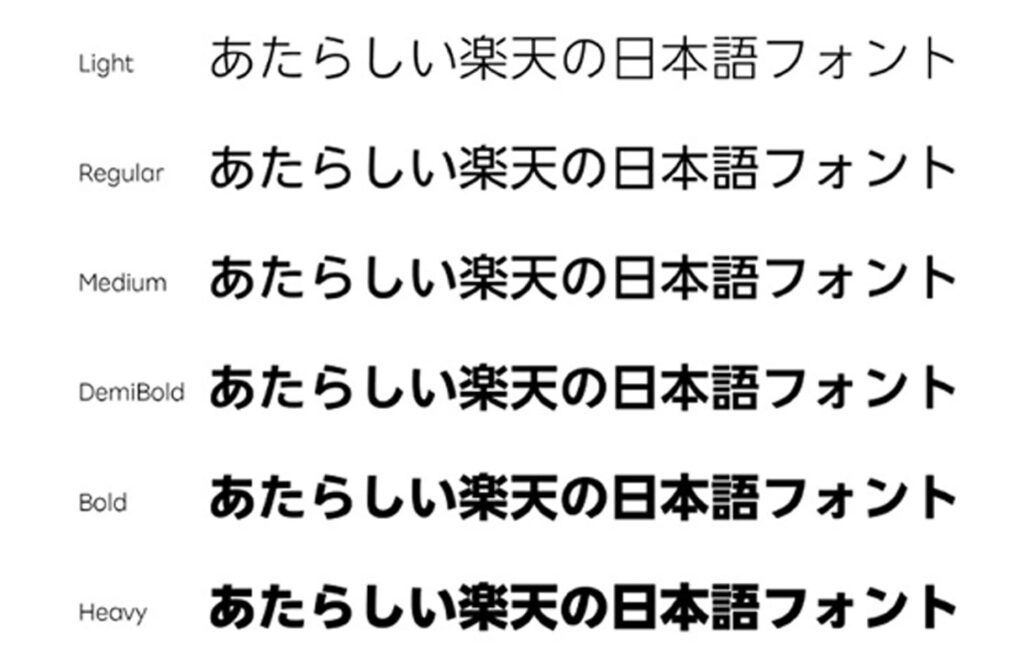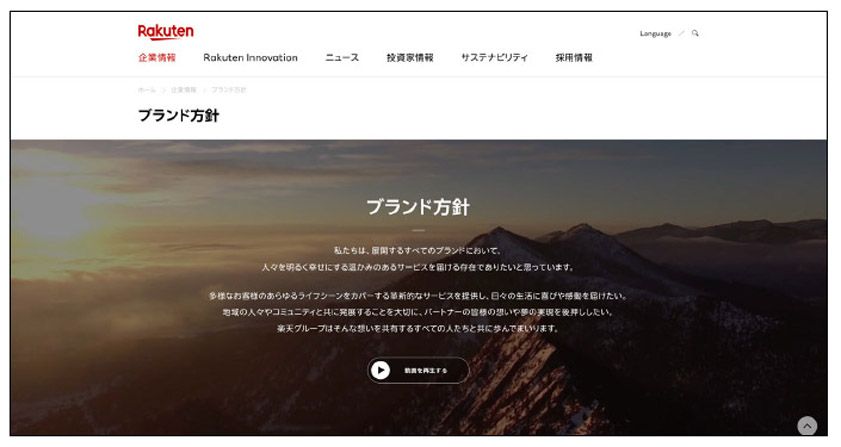
モリサワ 楽天の日本語コーポレートフォント「Rakuten Sans JP」を共同開発、コーポレートサイトに実装
株式会社モリサワは、楽天グループ株式会社とともに、日本語コーポレートフォント「Rakuten Sans JP」を共同開発した。「Rakuten Sans JP」は3月から、楽天のコーポレートサイトの一部で使用されている。
楽天は、国内外において、Eコマース、トラベル、デジタルコンテンツなどのインターネットサービス、クレジットカードをはじめ、銀行、証券、電子マネー、スマホアプリ決済といったフィンテック(金融)サービス、携帯キャリア事業などのモバイルサービス、さらにプロスポーツといった多岐にわたる分野で70 以上のサービスを提供。楽天会員を中心とした独自のメンバーシップを有機的に結びつけることで、独自の「楽天エコシステム(経済圏)」を形成しています。また、「イノベーションを通じて、人々と社会をエンパワーメントする」というミッションのもと、ユーザーや社会に向けてさまざまなメッセージを発信してきた。
そのブランド価値の向上を図る一環として、2020 年に開発された欧文コーポレートフォント「Rakuten Font」と、モリサワが提供する「UD 新ゴNT」の日本語フォントが主に運用されてきた。
そしてこの度、日本語での情報発信においても、より一層ブランドの統一感を表現するため、日本語コーポレートフォントの開発も行うこととなり、楽天グループの戦略的ブランディングにおいてクリエイティブ面をリードする組織「楽天デザインラボ」および多数のコーポレートフォント開発実績もあるモリサワとの共同開発が実現した。
「Rakuten Sans JP」は、欧文コーポレートフォント「Rakuten Font」のサンセリフ書体である「Rakuten Sans」との親和性を持たせながら、チーフクリエイティブデザイナー佐藤可士和氏の監修のもと、楽天のブランド方針やTone of Voice を体現するデザインとなっている。
これまで使用されてきた「UD 新ゴNT」をベースに、欧文エリアを「RakutenSans」に合わせ、すべてのかなに独自のデザインを施すことで、オリジナリティとこれまで通りの読みやすさを追求した。社名である「楽」「天」の漢字2 文字の字形も、楽天ブランドのアイデンティティを表現するものとして、細部にこだわって新たにデザインをしている。また、濁点の重なり方が異なる文字のバリエーションを導入し、使用するシーンによって使い分けを可能にするなど、可読性への配慮と使いやすさを両立。
その他の漢字も、想定される使用シーンに合わせてウエイトごとに字面を調整し、カスタマイズしています。
「Rakuten Sans JP」は楽天のコーポレートサイトなどで使用されるほか、その他のサイトや各種アプリ、IR 資料などで広く活用される予定。